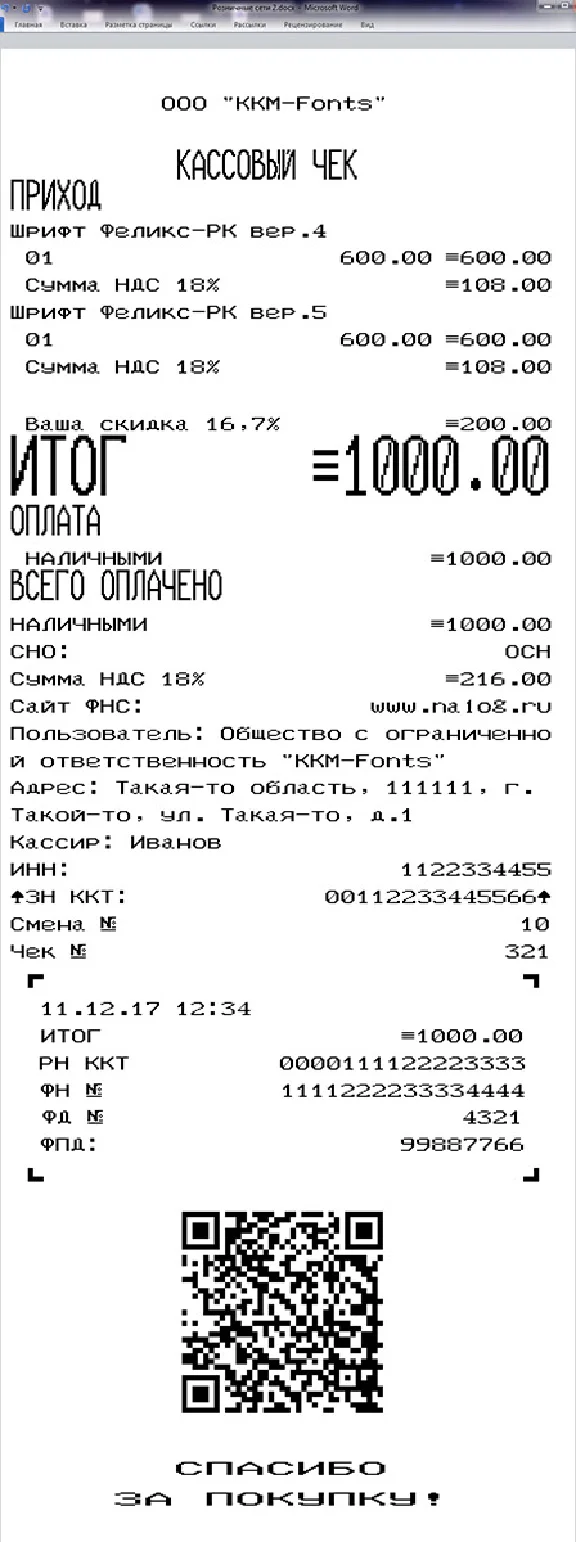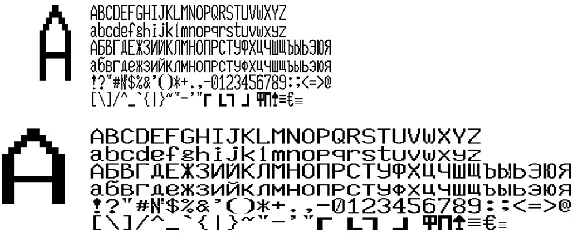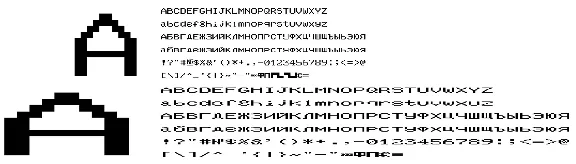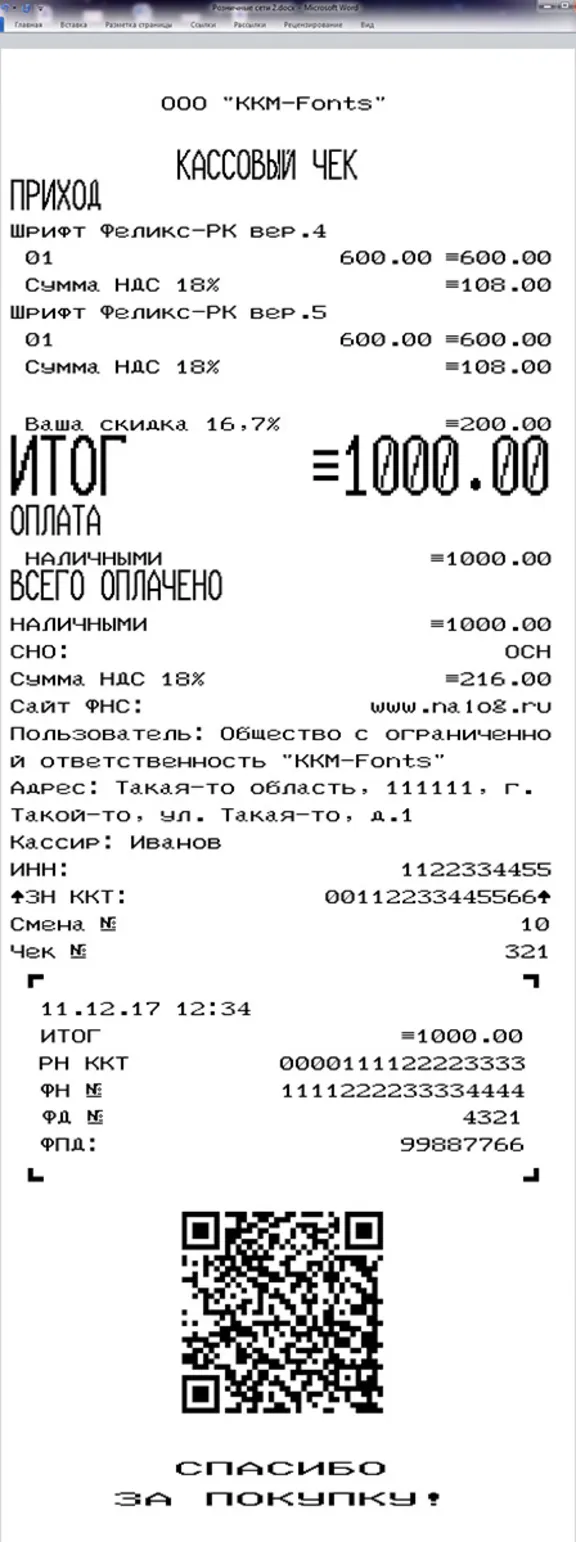
Данный набор шрифтов "Розничные сети 2" кассового аппарата ФЕЛИКС-РК содержит 2 версии шрифтов (4 и 5) в формате TTF (русские и английские буквы) для использования в программе Microsoft Word. В архиве находятся стандартные и широкие шрифты для каждой версии (всего 4 шрифта) в формате TTF и шаблон варианта чека, который, в частности, используется во многих сетях магазинов розничной торговли, например "Рубль Бум". Вам остается только установить шрифты в систему (обычно C:\WINDOWS\Fonts), открыть шаблон и начать редактирование. Печатать чеки предпочтительно на термопринтере, на кассовой термоленте. Хотя можно печатать и на струйнике и лазерном, с возможностью вывода на факсовую бумагу. Лучшее качество, естественно, при печати на термопринтерах.